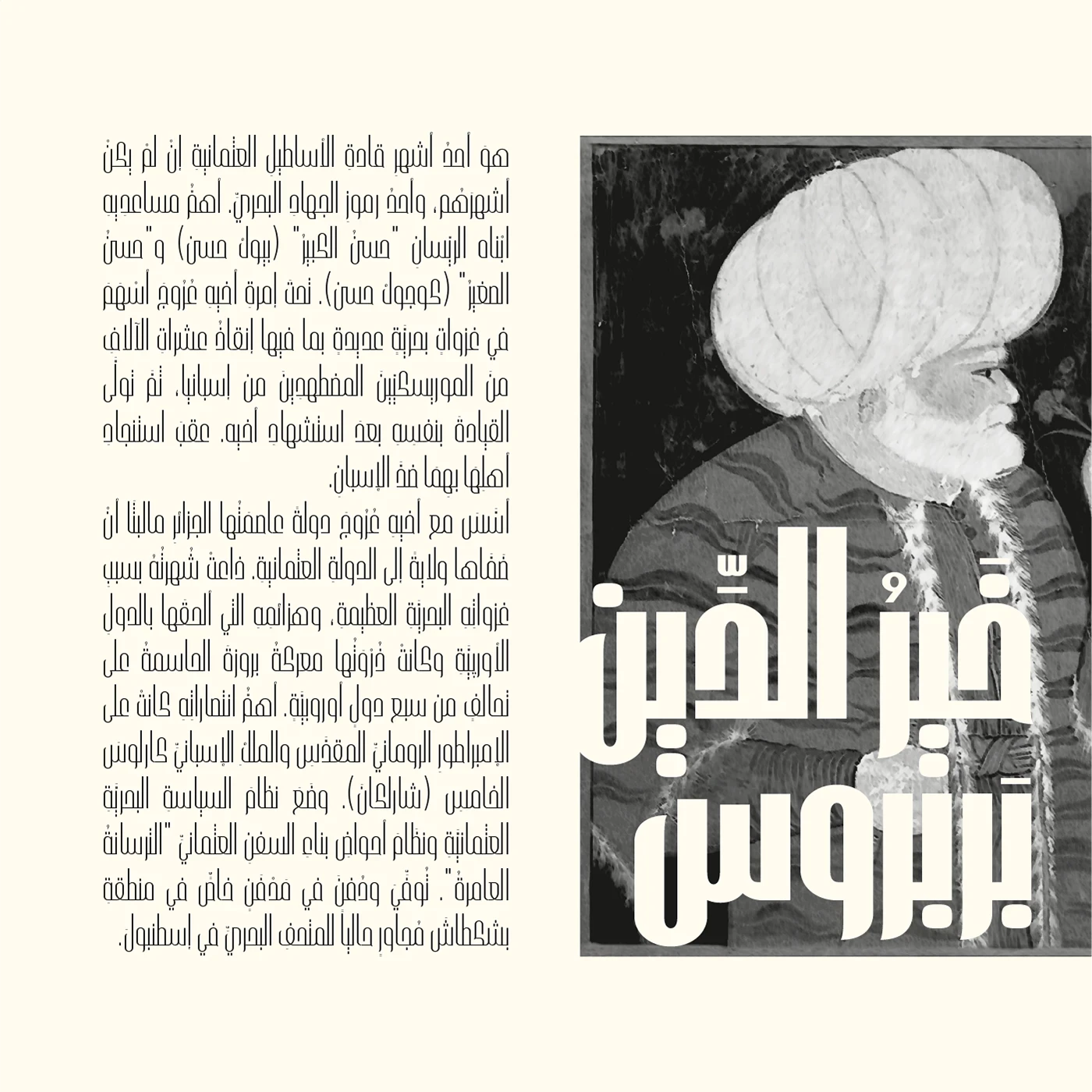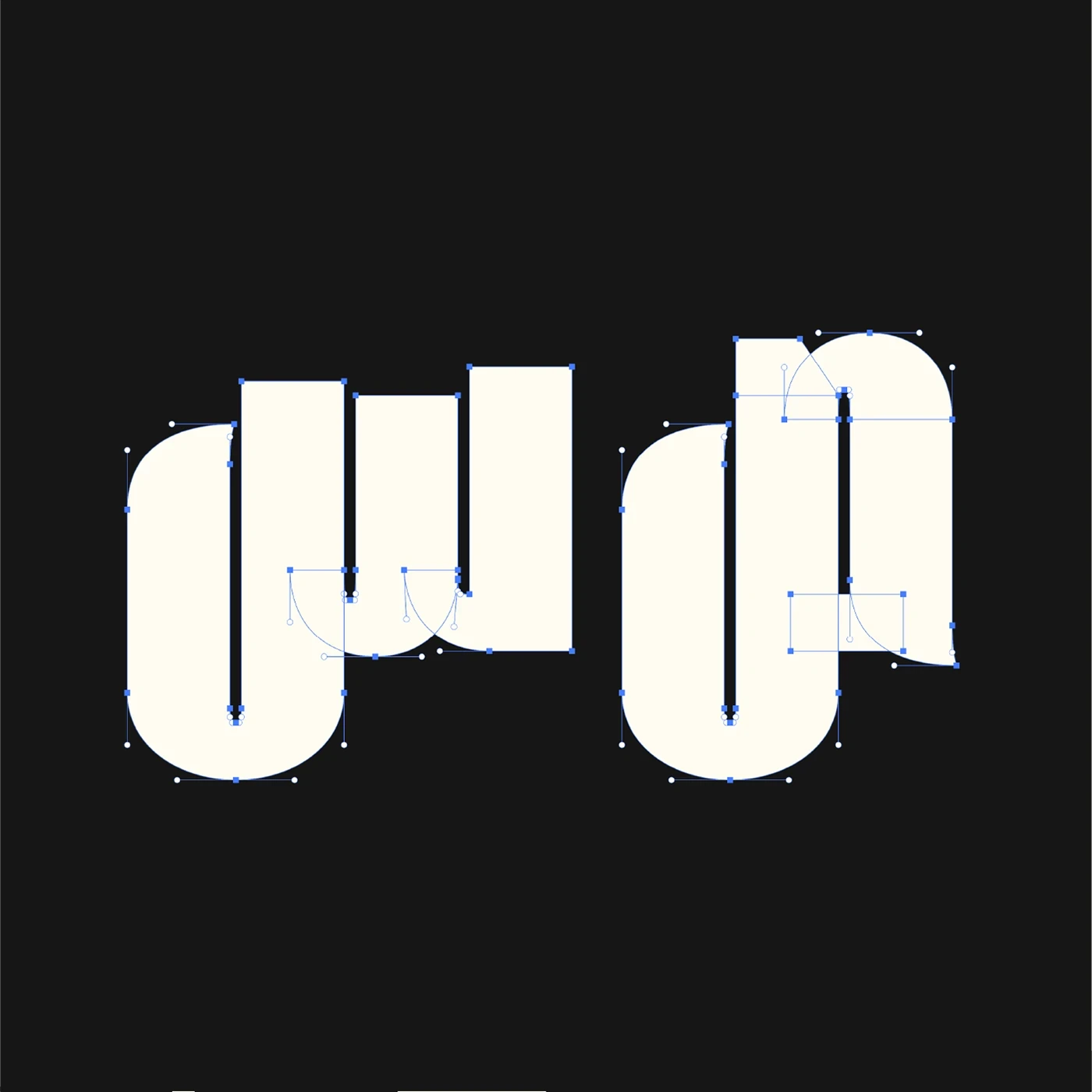
خط عرض مضغوط بأسلوب آرت ديكو بدون سن (Sans)، يحتوي على 8 أنماط، وأكثر من 800 رمز (Glyph)، وأكثر من 100 تركيبة (Ligature)، ويدعم أكثر من 30 لغة، بالإضافة إلى العديد من ميزات OpenType.
يُعد مثاليًا لتصميم الملصقات، المجلات، أغلفة الكتب، الشعارات، العناوين، الصحف، والمطبوعات الصحفية.
يتميز بأنه جريء، عصري، هندسي، ويغطي مجموعة واسعة من الأوزان من الخفيف إلى السميك جدًا.